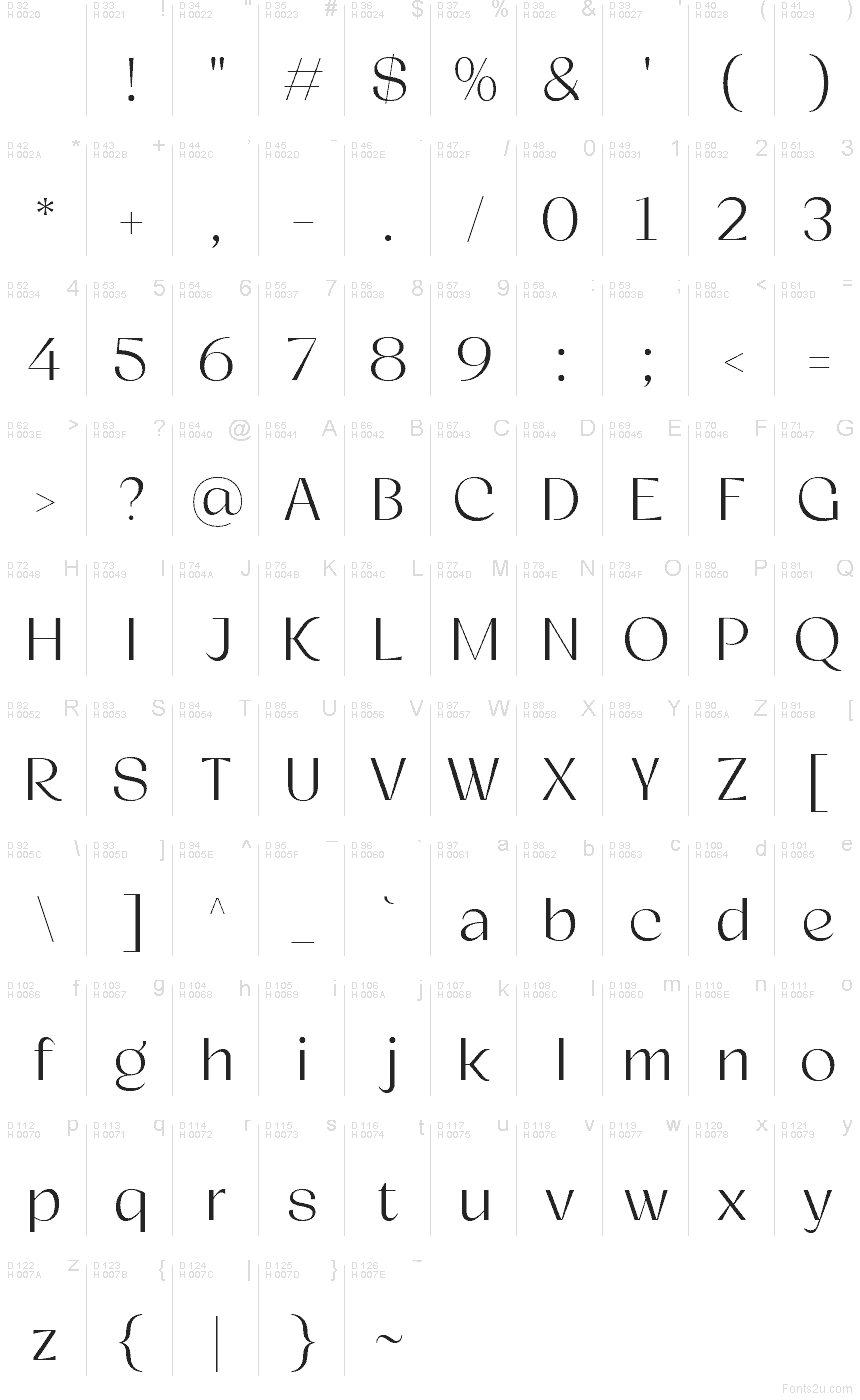
Relicta Light, autorstwa Jehoo Creative, to darmowy, nowoczesny krój szeryfowy o wysokim kontraście, utrzymany w klimacie modowego edytorialu. Litery są pełne lekkości i wdzięku, łącząc niezwykle cienkie linie z szerokimi, zamaszystymi łukami i eleganckimi łączeniami, co nadaje krojowi wyrafinowany, niemal dramatyczny rytm.
Świetnie sprawdza się w nagłówkach magazynów, opakowaniach kosmetyków, brandingu butików, tytułach zaproszeń oraz na okładkach książek, gdzie darmowy font z tak silnym kontrastem potrafi samodzielnie zdefiniować stronę. Użyj go w krótkich nagłówkach, tekstach na okładkach lub inicjałach w stylu monogramu, gdy zależy Ci na eleganckim napięciu między delikatnymi liniami a szerokimi, pełnymi gracji łukami.